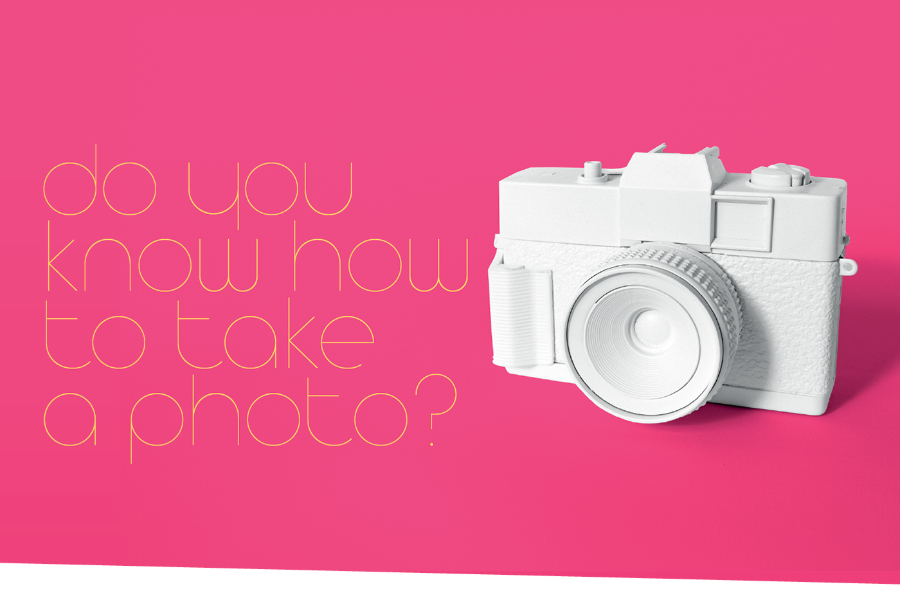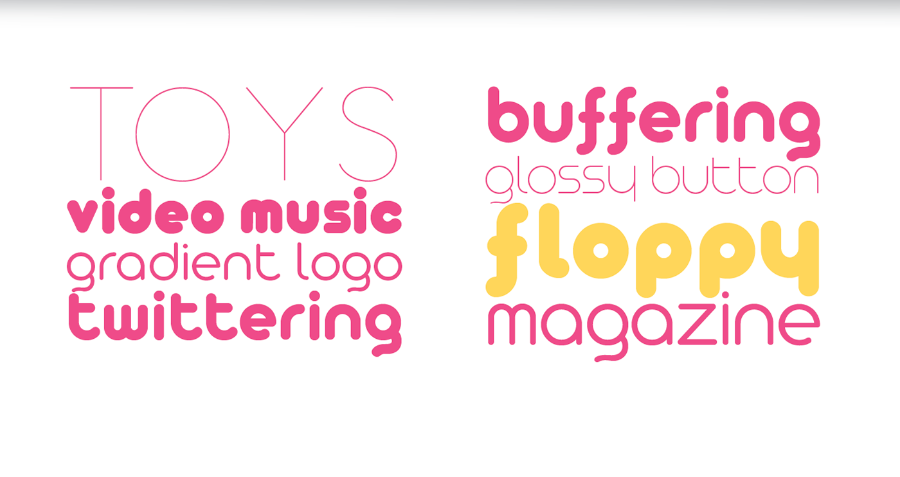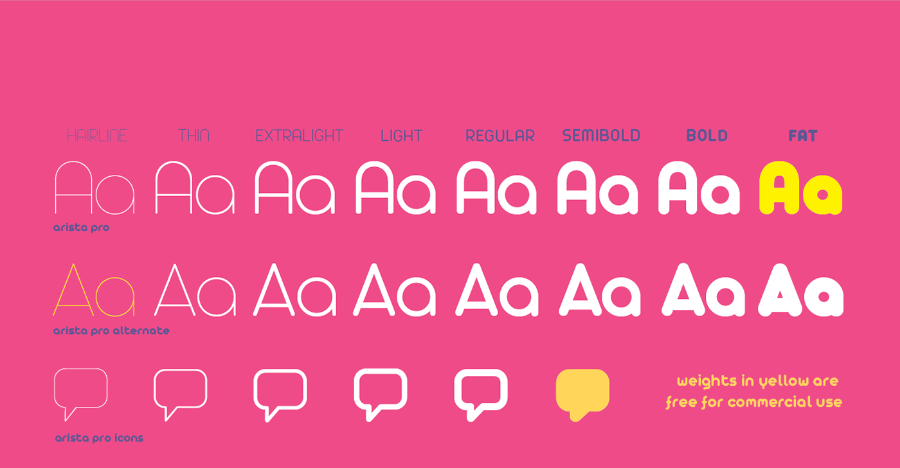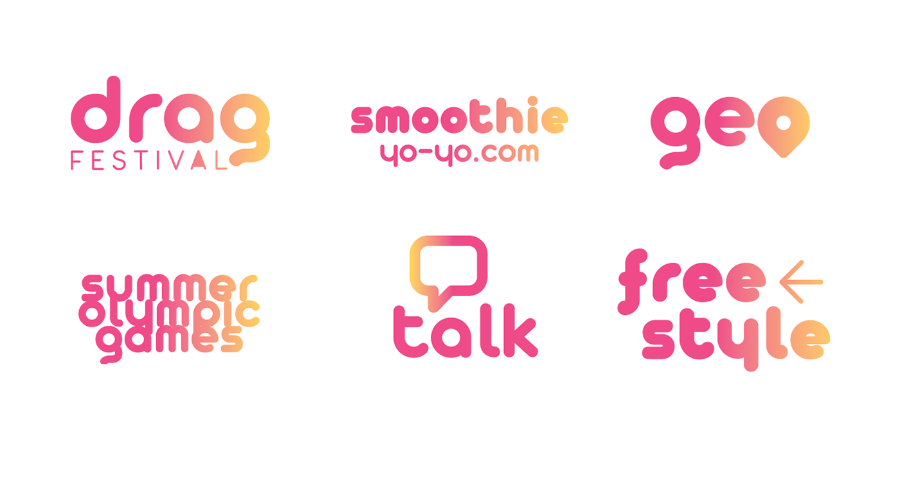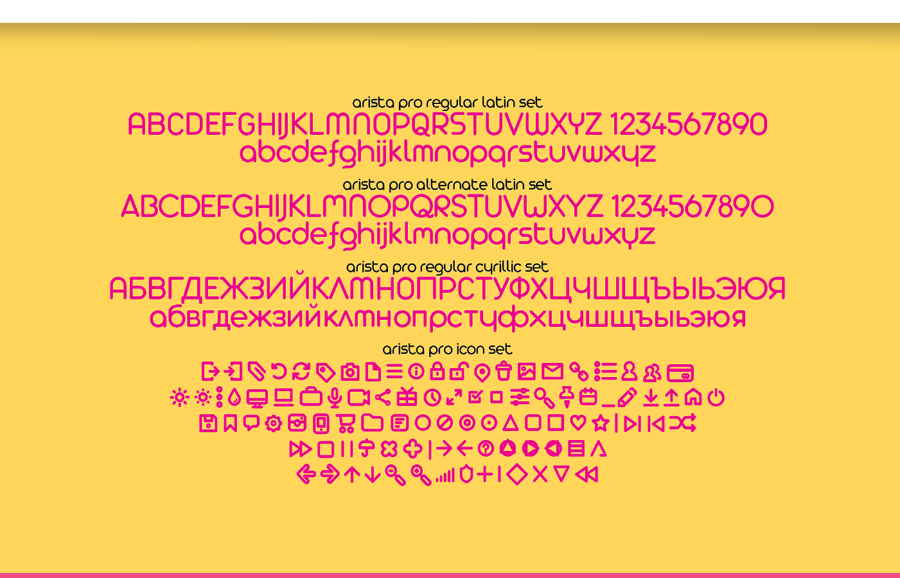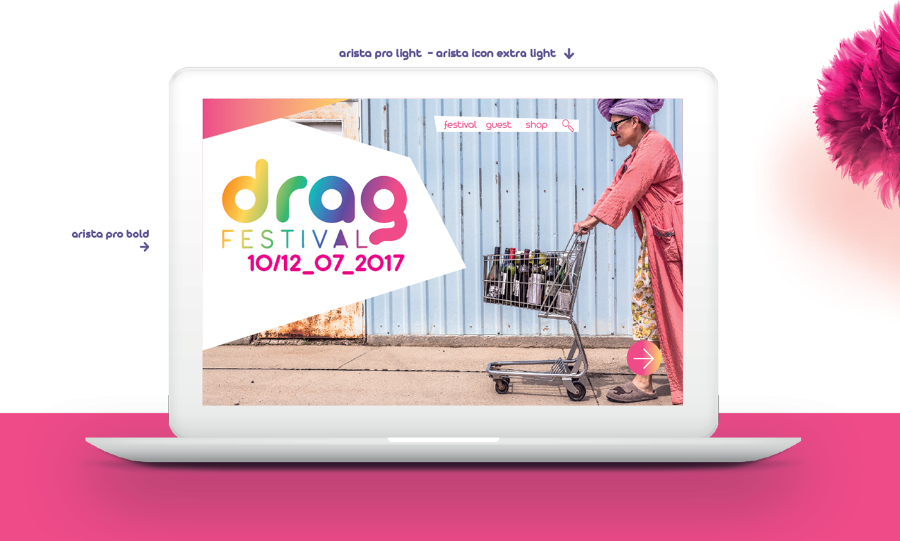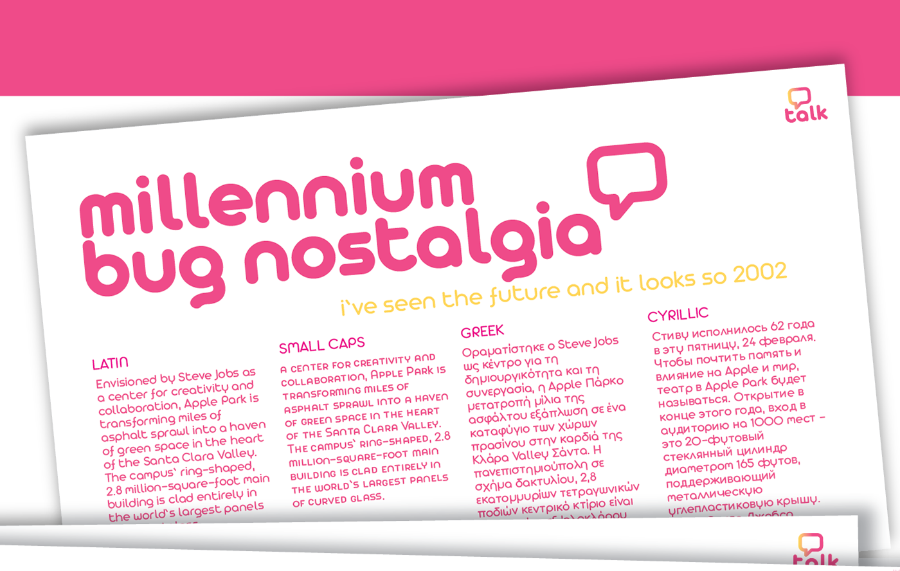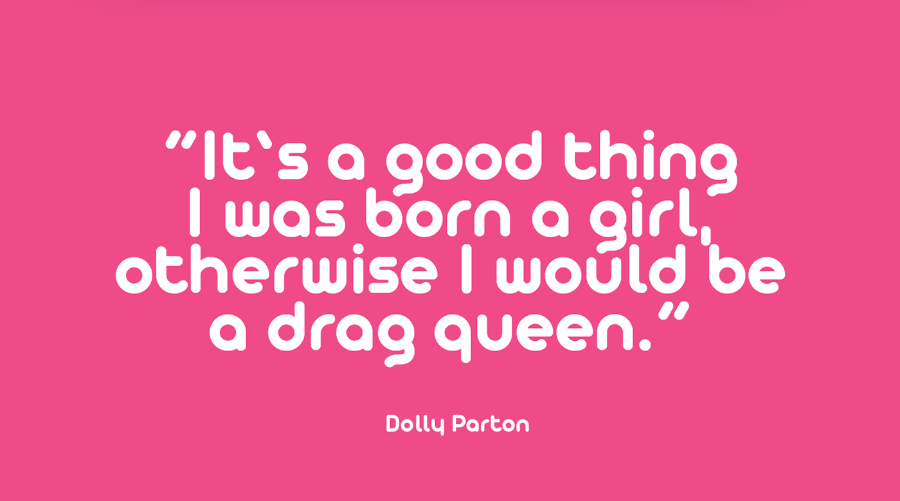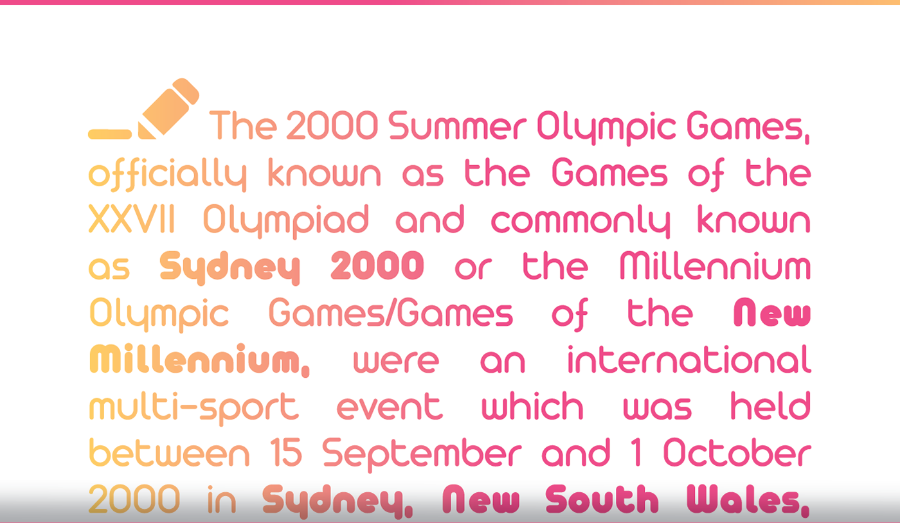
Arista Pro免费演示字体
Arista Pro免费演示字体由弗朗切斯科·卡诺瓦罗(Francesco Canovaro)成功完成的Arista字体的最终版本的一部分。这个专业版的Arista具有原始字体的几何和柔和的特点。但这一次,它有一个全面的权重和两个替代版本。此外,它还包括了希腊文,西里尔文和拉丁文字。伴侣图标字体,Arista Pro Icon允许可变宽度monoline图标,非常适合与字体线条宽度匹配。所以,在这里下载试用家庭和两个自由的权重,让自己一些灵感!